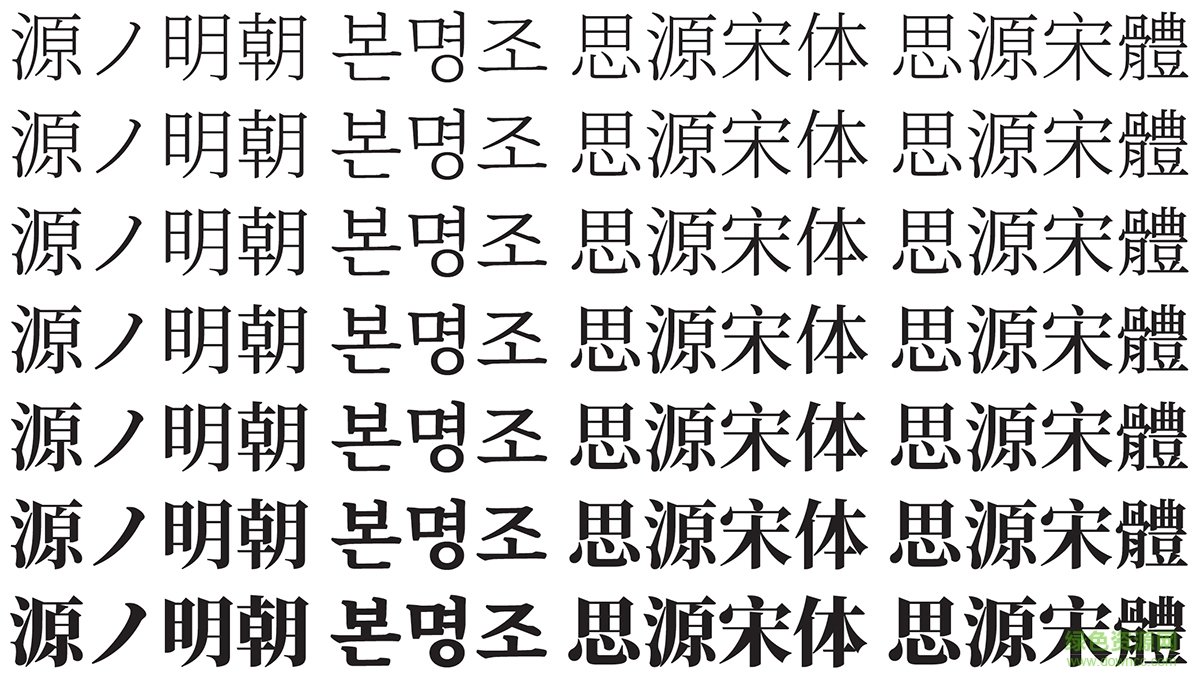
思源宋體ttf是谷歌全新推出的google開源字體,支持簡(jiǎn)體中文、繁體中文、日語(yǔ)和朝鮮語(yǔ)四中語(yǔ)言,大氣優(yōu)美更有藝術(shù)感,大家快來(lái)綠色資源網(wǎng)搶先嘗試吧!
谷歌和adobe于2017年3月3日以「SIL開放字體許可證」 開源發(fā)行了字體「思源宋體」(Source Han Serif,Google 稱 Noto Serif CJK),旨在為東亞 15 億人口提供統(tǒng)一的字體。官方文檔顯示,思源宋體包含了簡(jiǎn)繁日韓四種漢字寫法,七種粗細(xì)字重,共收錄 458745 個(gè)字型。
思源宋體支持四種不同的東亞語(yǔ)言(簡(jiǎn)體中文、繁體中文、日語(yǔ)和朝鮮語(yǔ)),7 種粗細(xì)類型中的每一種都有 65535 個(gè)字形,像幾年前推出的思源黑體(Source Han Sans)一樣,思源宋體針對(duì)屏幕顯示進(jìn)行了優(yōu)化,但顯得更加優(yōu)雅,更具有文藝性,可共同呈現(xiàn)一致的視覺(jué)美感。該字體還包含多個(gè)西方字形,支持拉丁語(yǔ)、希臘語(yǔ)和西里爾文腳本,這些字形均來(lái)源于 Source Serif。